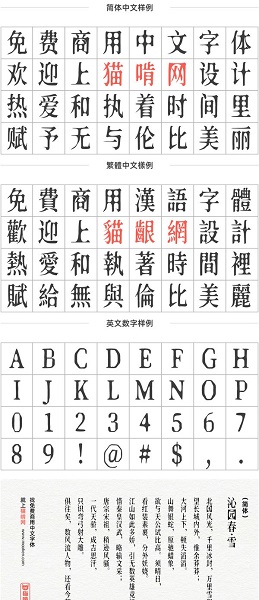
新愚公滄桑體給喜歡各種不同字體的朋友帶來完全免費(fèi)且具有滄桑感的中文字體,線條優(yōu)美簡(jiǎn)潔大氣具有濃厚的國(guó)風(fēng)氣息,讓你的電腦字體與眾不同感受不同字體的美,簡(jiǎn)單的操作方式就可以輕松替換等你來下載。
新愚公滄桑體是一款充滿斑駁感覺的字體,基于思源宋體改造,加入了隨機(jī)的扭曲效果,讓這款字體蒙上了一種歲月的斑駁滄桑感,這款扭扭曲曲的字體,也適合用于類似古印字體的設(shè)計(jì)、